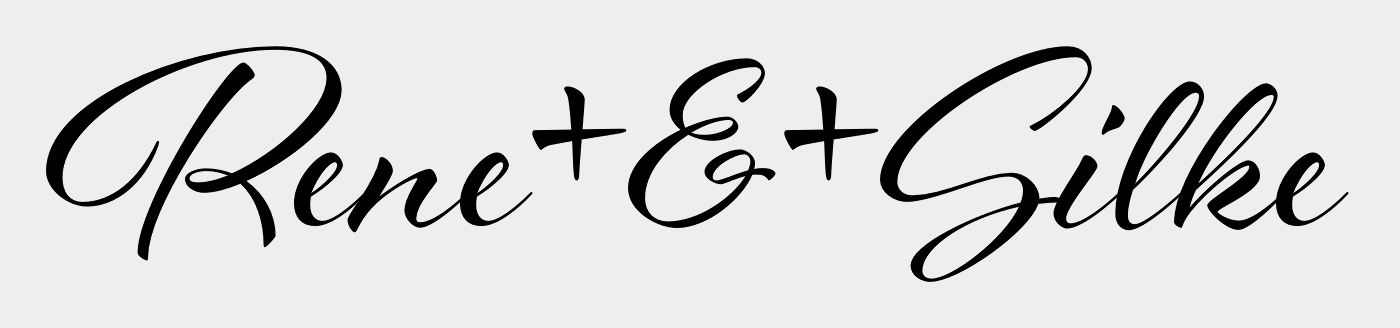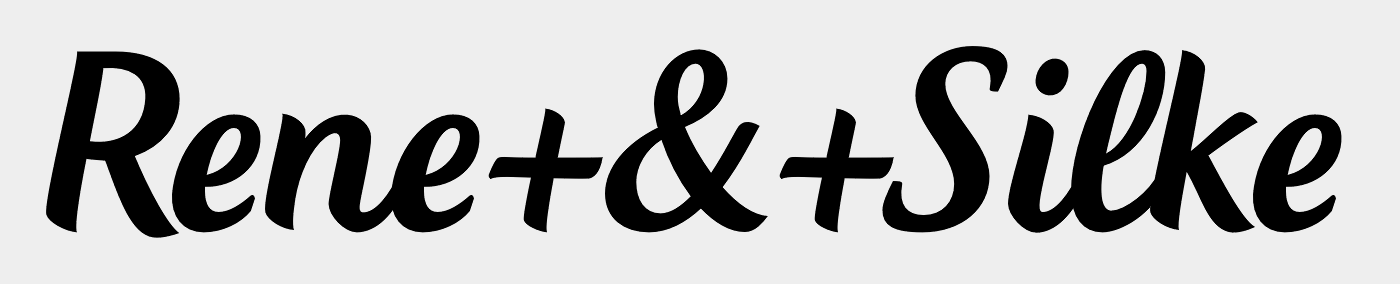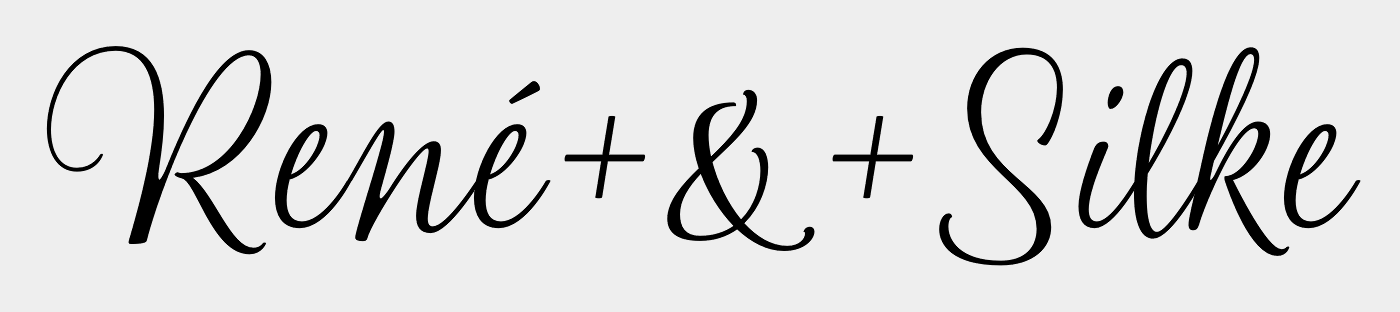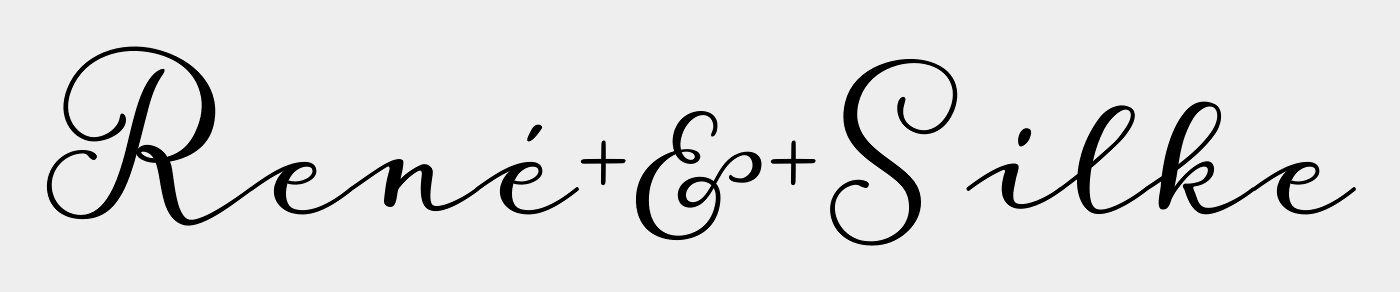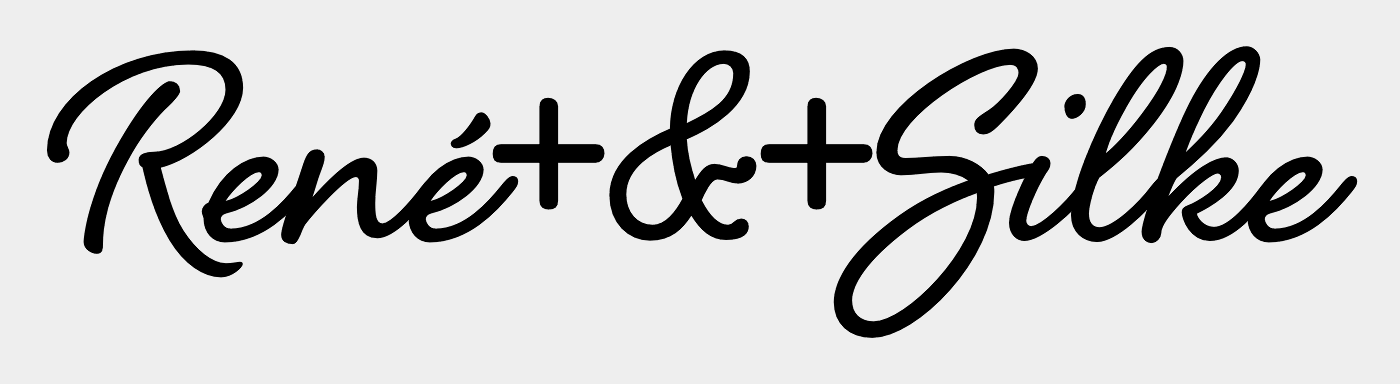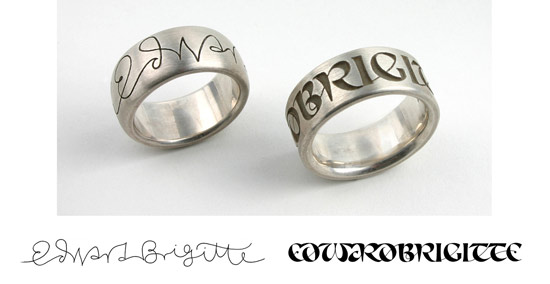
Ehe-Ringe Gravur-Schrift
Ich hoffe ihr könnt mir ein wenig weiterhelfen: Ich bin auf der Suche nach einer schönen schwungvollen Schrift für unsere Ehe-Ringe.
Da mir die Standard-Schriften des Juweliers nicht besonders zusagen möchte ich gerne eine Laser-Gravur mit eigenem Charakter.
Die Gravur umfasst folgenden Text: "René & Silke 6.8.2016"
Die gesamte Schrifthöhe liegt bei max. 4 mm.
Besonders wichtig ist mir natürlich eine gute Lesbarkeit, gibt es da bei einer Gravur etwas besonderes zu beachten?
Ich möchte aber auf jeden Fall eine schwungvolle Schrift, keine Serif oder Sans Serif. Es sollte allerdings keine allzubrave oder schnörkelige Schreibschrift sein. Da ich die Schrift tatsächlich ausschließlich für den persönlichen Gebrauch für eben diese eine Gravur benötige, würde ich einen kostenlosen Font bevorzugen.
Habt ihr hierzu vielleicht ein paar Ideen?
Meine erste Idee wäre, den Juwelier zu fragen, was er denn überhaupt umsetzen kann. Beim Lasergravieren kann auch die eigene Handschrift graviert werden, da muss auf gar keine bestehende Schrift zurückgegriffen werden. Noch persönlicher geht’s dann nicht.
Ja, Handschrift ist mit Laser-Gravur möglich.
Das haben wir uns auch schon überlegt, aber dagegen entschieden.
Wenn schon Laser-Gravur, dann kann man auch solche tollen Sachen machen, die der geschätzte Kollege Hoyer anbietet :-o;-)
Man sieht hier auch schon, was alles möglich ist, und das selbst feine Linien gut funktionieren. Ich würde keine allzu ausufernden Ober- und Unterlängen verwenden und für die Lesbarkeit ruhig eine Schrift mit kräftigen Linien wählen.
Aber von ...
... bis ...
... sollte einiges möglich sein.
Vielleicht ist ja auch was bei der geschätzten Laura Worthington bei :-?;-)
Zum Beispiel die Shelby ...
Die eigene Handschrift zu verwenden finde ich schön – das habe ich auch schon mal gemacht bei einem Ring*. Und wenn man die eigene Handschrift mangels Eignung nicht verwenden will, kann man auch eine Kalligrafen beauftragen. Der Kollege Schnitzel hier aus dem Forum wäre der optimale Ansprechpartner dafür.
*Nachtrag: Hier der Link zum Ring.
Da ich die Schrift tatsächlich ausschließlich für den persönlichen Gebrauch für eben diese eine Gravur benötige, würde ich einen kostenlosen Font bevorzugen.
Nur mal so als ganz behutsamen Denkanstoß: Gehst du mit dieser Haltung auch zu deinem Juwelier? Dem Konditor der Hochzeitstorte? Dem Wirt des Hochzeitslokals? Viele der Schriftexperten, die sich hier tummeln, entwickeln und verkaufen selbst Schriften; damit bestreiten sie Teil ihres Lebensunterhalts.
Die oben genannte Storyteller kostet gerade mal 17 € und die Shelby 23 € – das sollte einem doch der ›eigene Charakter‹ mindestens wert sein. Man beabsichtigt ja eigentlich nur einmal zu heiraten und den Ring den Rest seines Lebens zu tragen.
Nur mal so als ganz behutsamen Denkanstoß: Gehst du mit dieser Haltung auch zu deinem Juwelier? Dem Konditor der Hochzeitstorte? Dem Wirt des Hochzeitslokals?
Hierzu möchte ich mich dennoch äußern: Juwelier, Konditor, Wirtschaft, Blumen, Hochzeitskleid, usw. – ich habe im Augenblick sehr viele Ausgaben. Ich bin aber kein Unternehmen, das ein Corporate Design umsetzen will, sondern Privatperson mit einem einmaligen persönlichen Einsatzzweck. Da ist der Geldbeutel leider nicht so dick und ich muss Prioritäten bei den Ausgaben setzen. Ich gebe euch vollkommen recht, dass Schriftentwickler von ihren Schriften leben können sollen, dennoch bitte ich auch einen Blick auf die Verhältnismäßigkeit zu werfen. Ich habe gesagt, ich würde einen kostenlosen Font bevorzugen. Wenn mir eine Schrift besonders gut gefällt und der Preis für mich bezahlbar ist, gebe ich auch gern das Geld dafür aus.
Ich hoffe, dass das jetzt nicht zu einer Grundsatzudiskussion anregt, mir ist die Problematik des Themas durchaus bewusst.
Die Ideen mit der Außengravur finde ich wirklich sehr schön.
Wir haben allerdings unsere Ringe schon gekauft und es geht nur um die Gravur auf der Innenseite.
Ich finde gut, was du schreibst!
Als jemand, der sich gerade mit der selben Planungsarbeit beschäftigt, kann ich das gut nachvollziehen. Man muss einfach das Geld nen bisschen zusammenhalten und für sich sind 30 Euro für nen Schriftschnitt nicht viel, aber bei so ner Hochzeit läppert es sich dann eben doch ganz schnell mal …
Dann wären vielleicht noch die Al Fresco von Laura Worthington oder die Creamy Script bedenkenswerte Alternativen.
Der Stil gefällt mir sehr gut!
Nur an dem "&" und dem "S" störe ich mich etwas.
Ich mag das amerikanische "&" nicht so gerne. Und ich finde das "S" schöner ohne die Verbindung zum "i".
Das hatte ich früher auch immer so gemacht – bis mich der Graveur mal aufgeklärt hat, dass er die Vektordaten ausdruckt, einscannt und seine Graviermaschine mit dem Bild füttert.